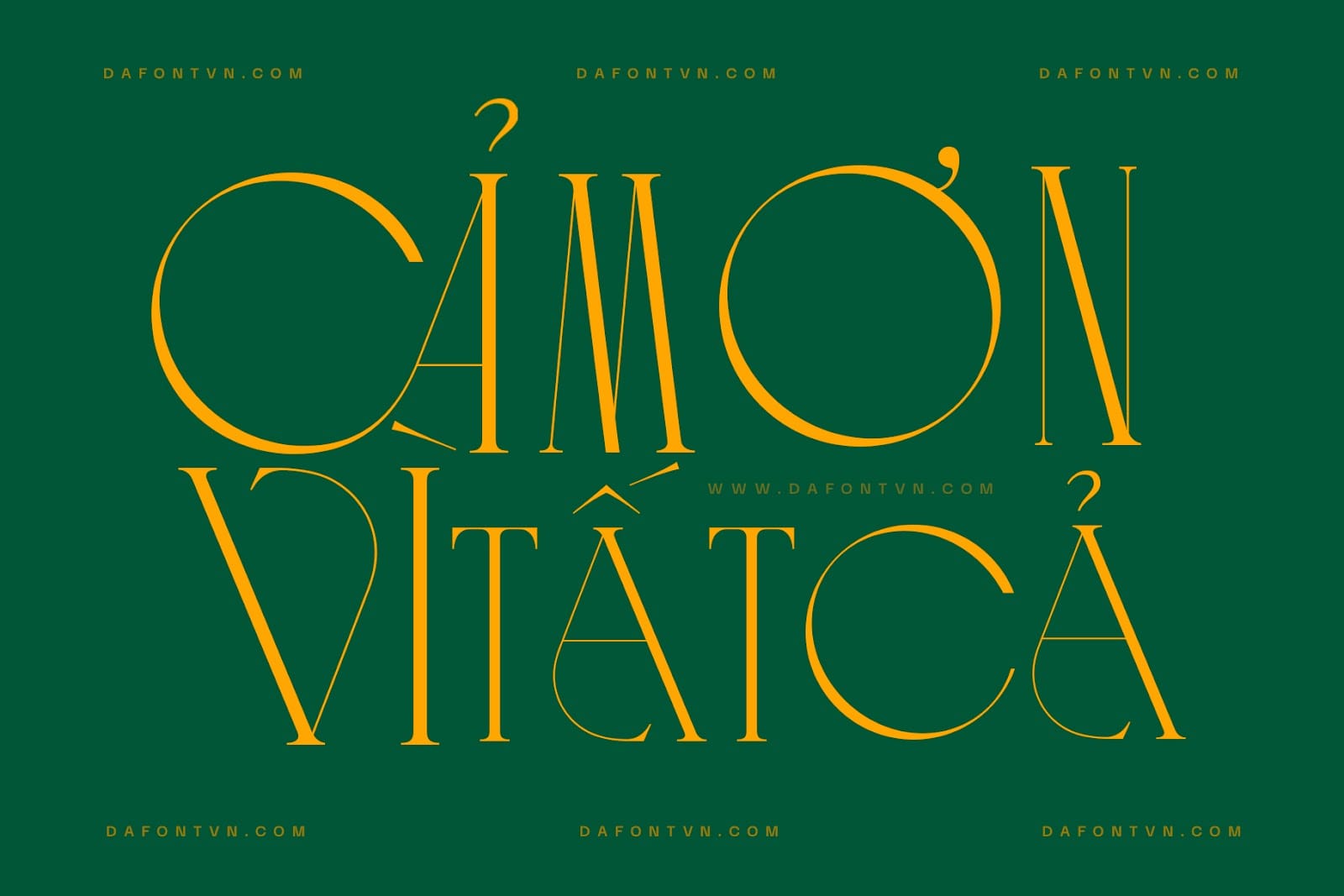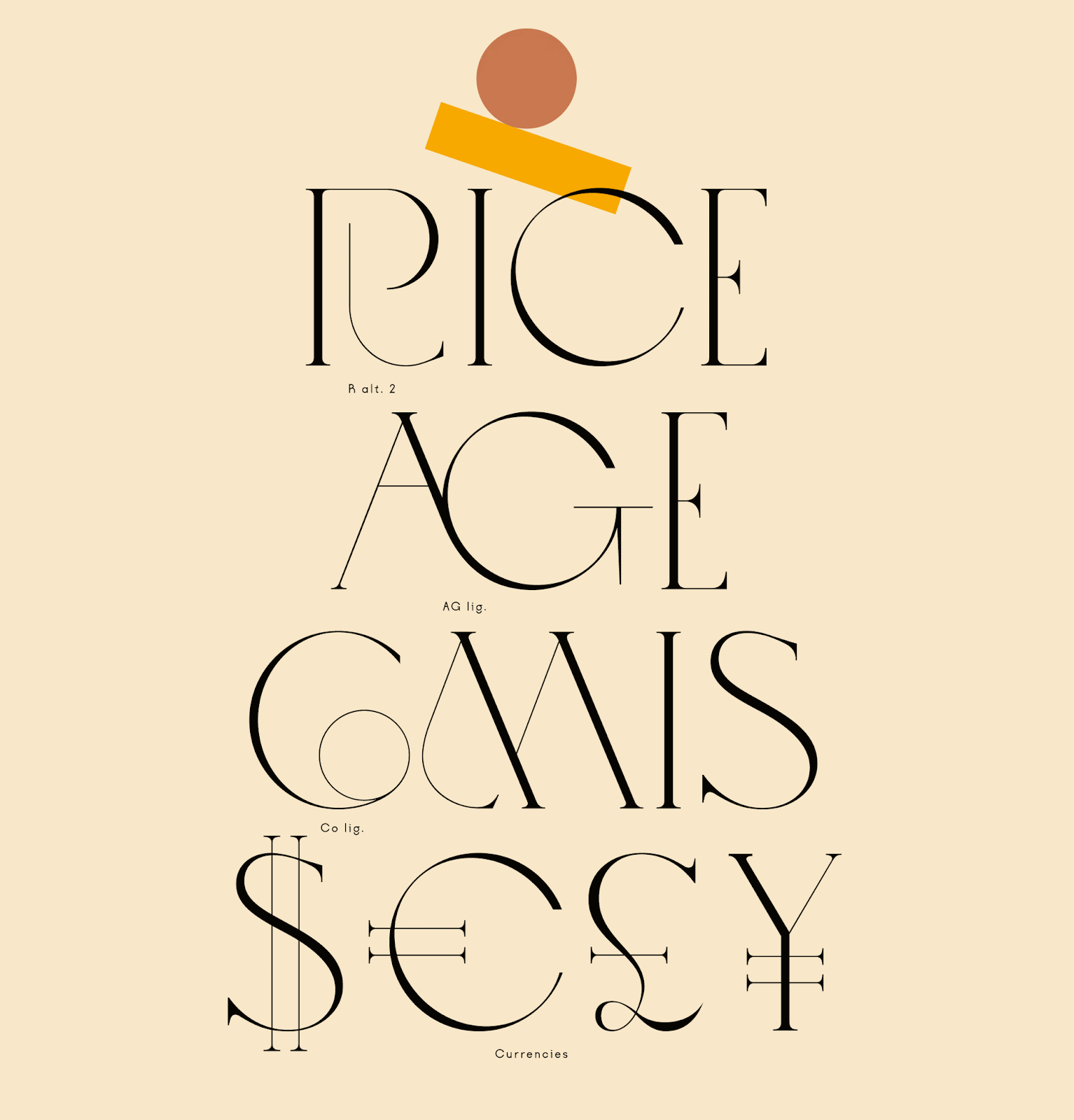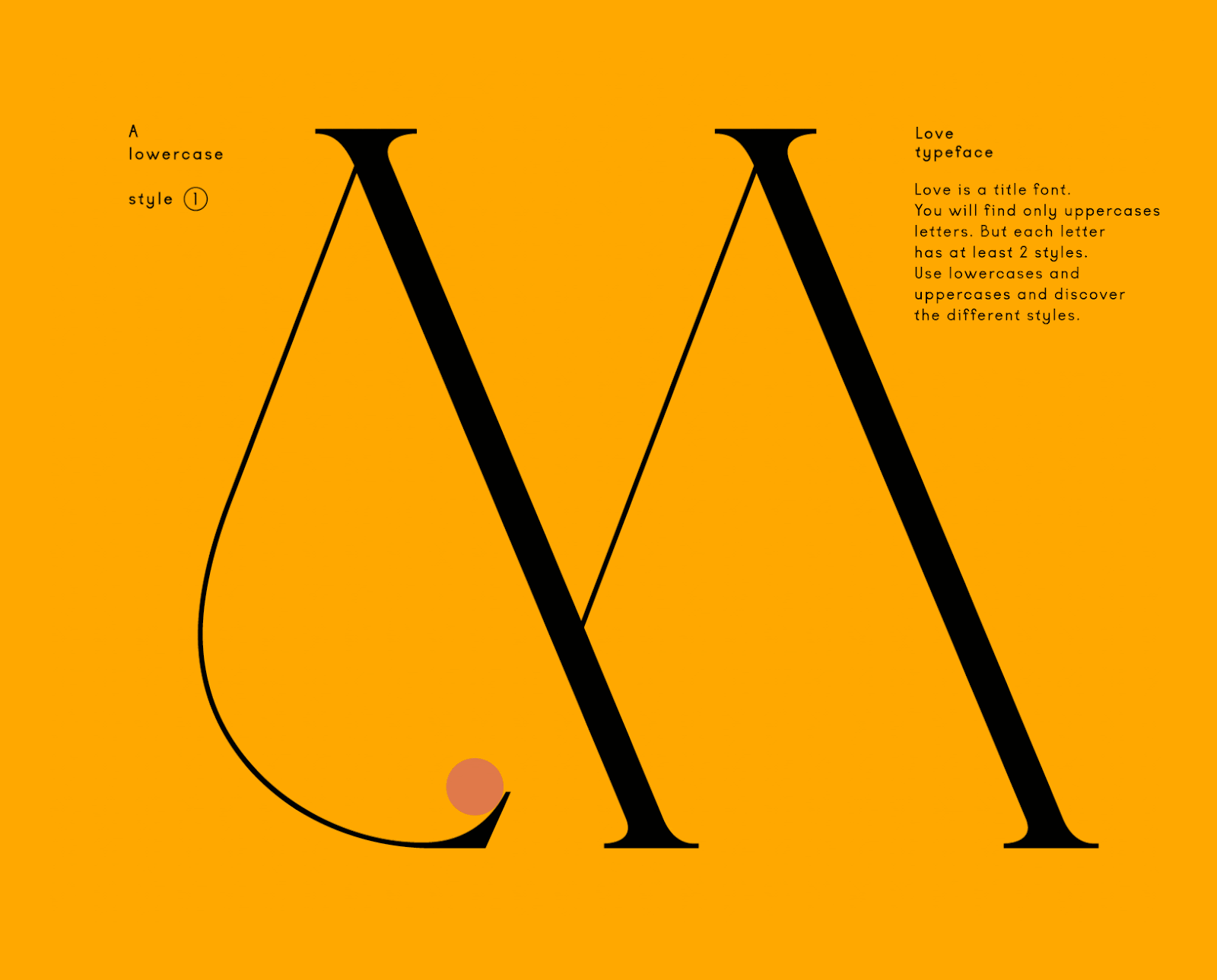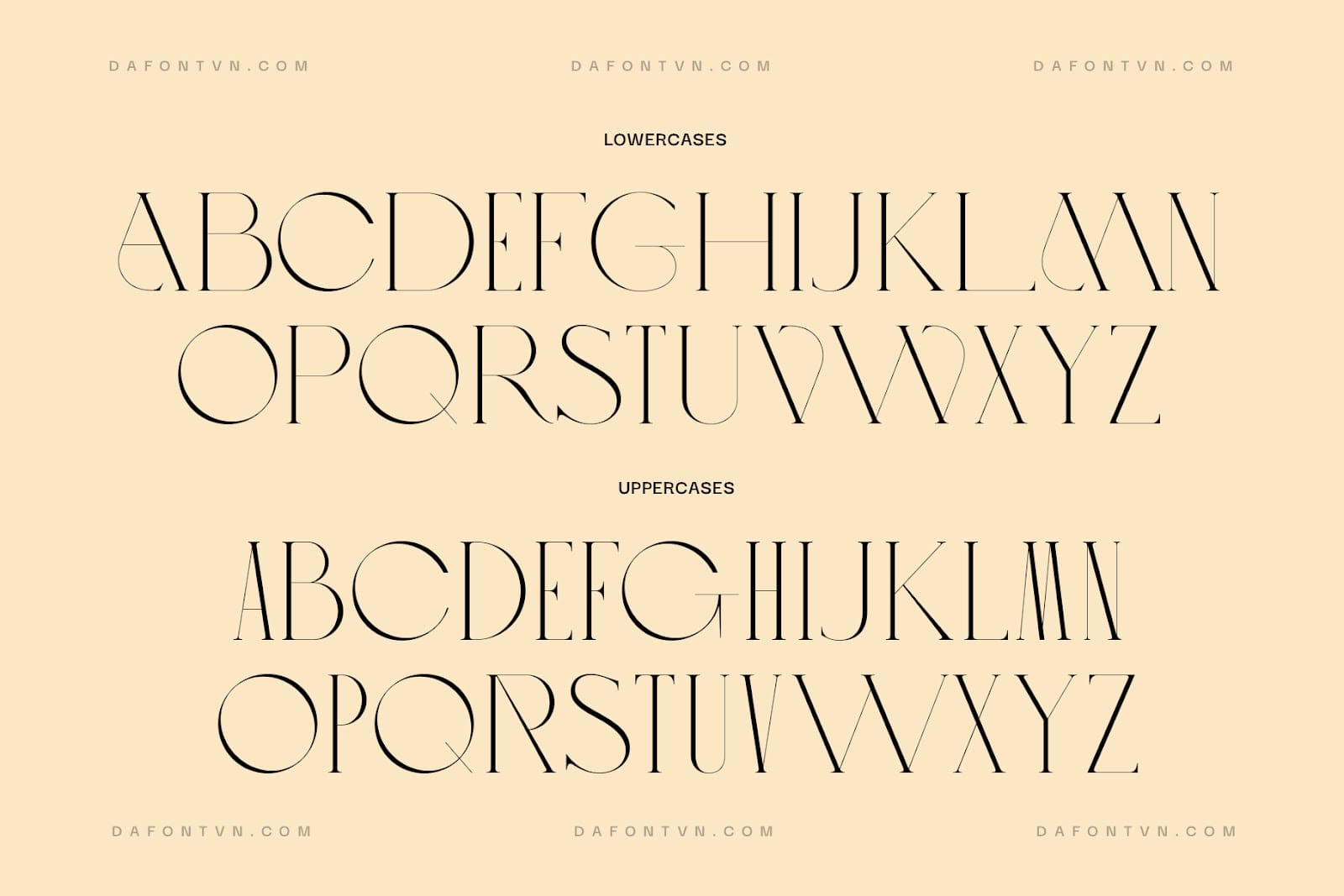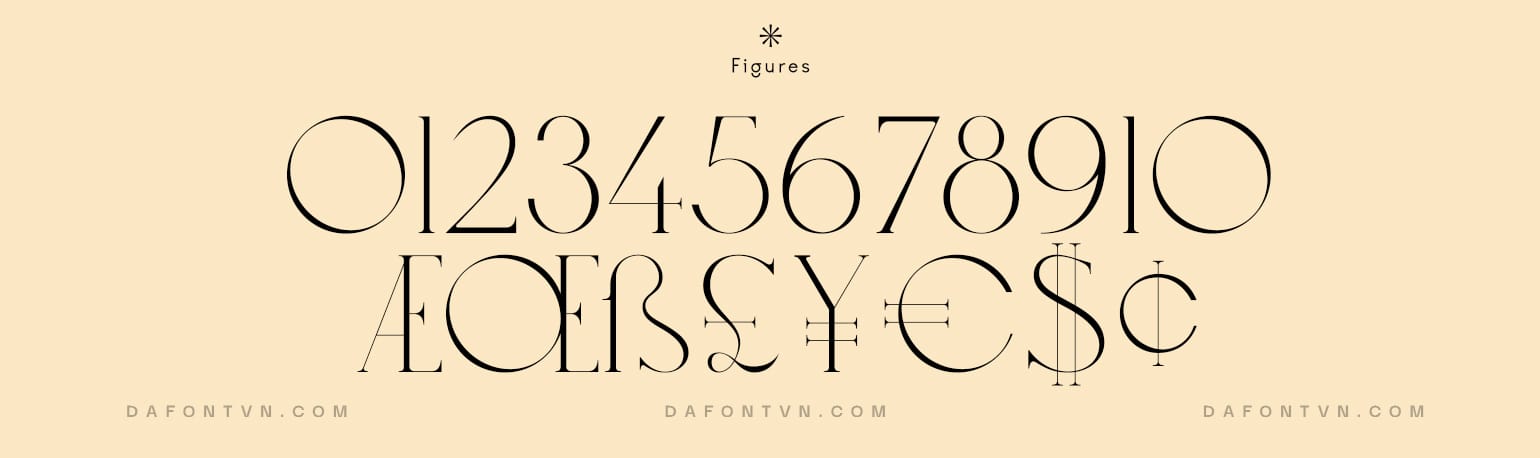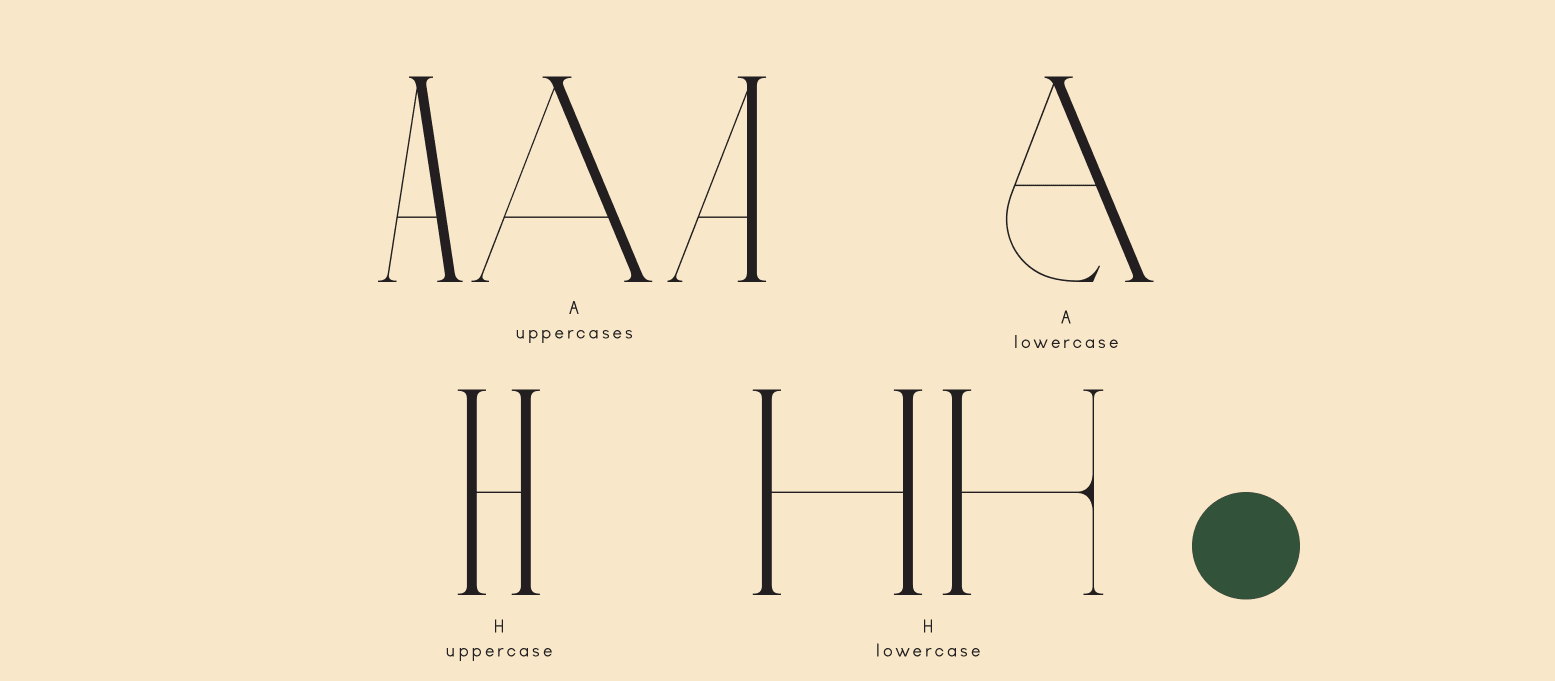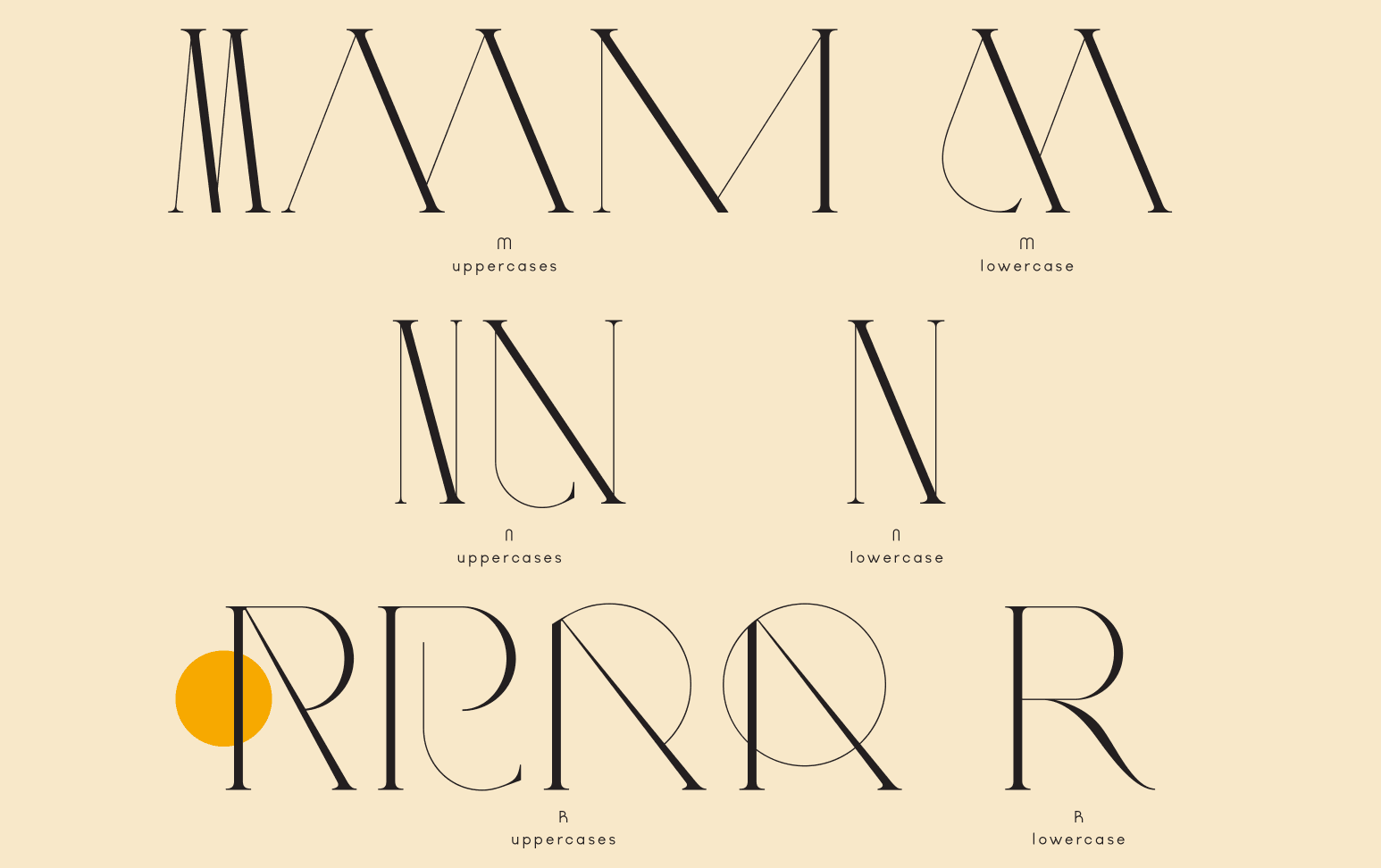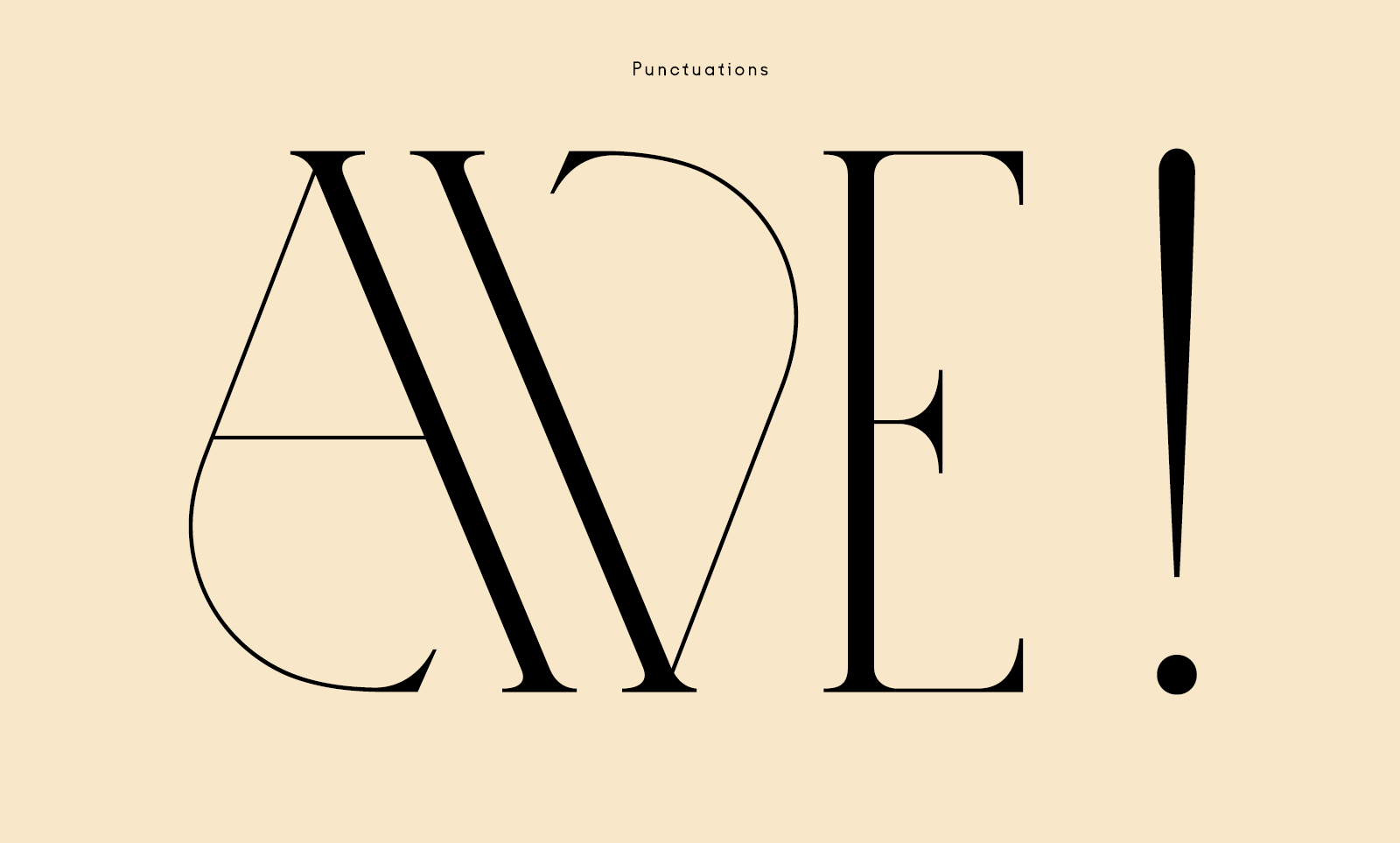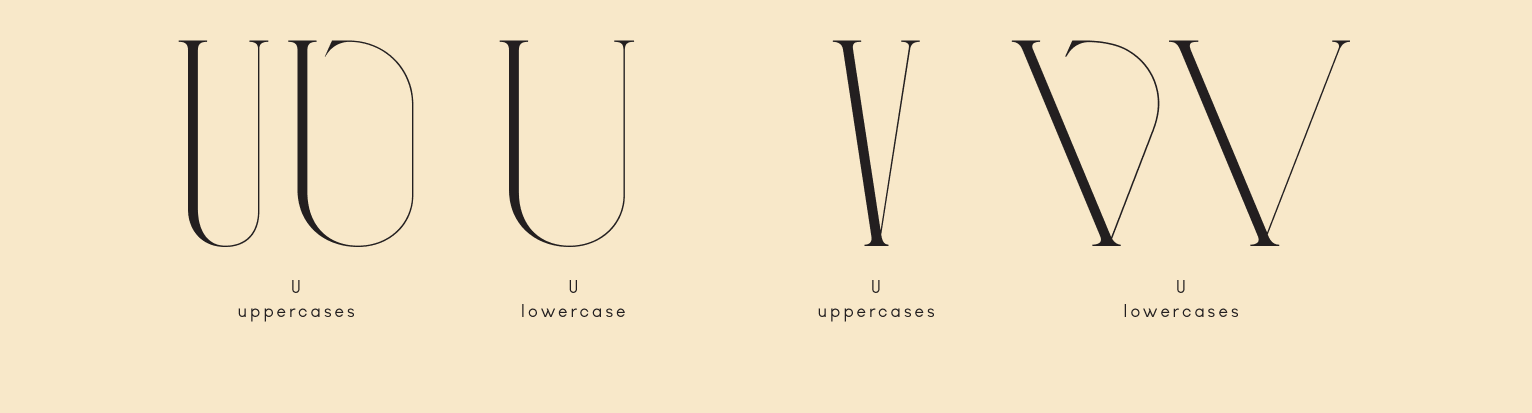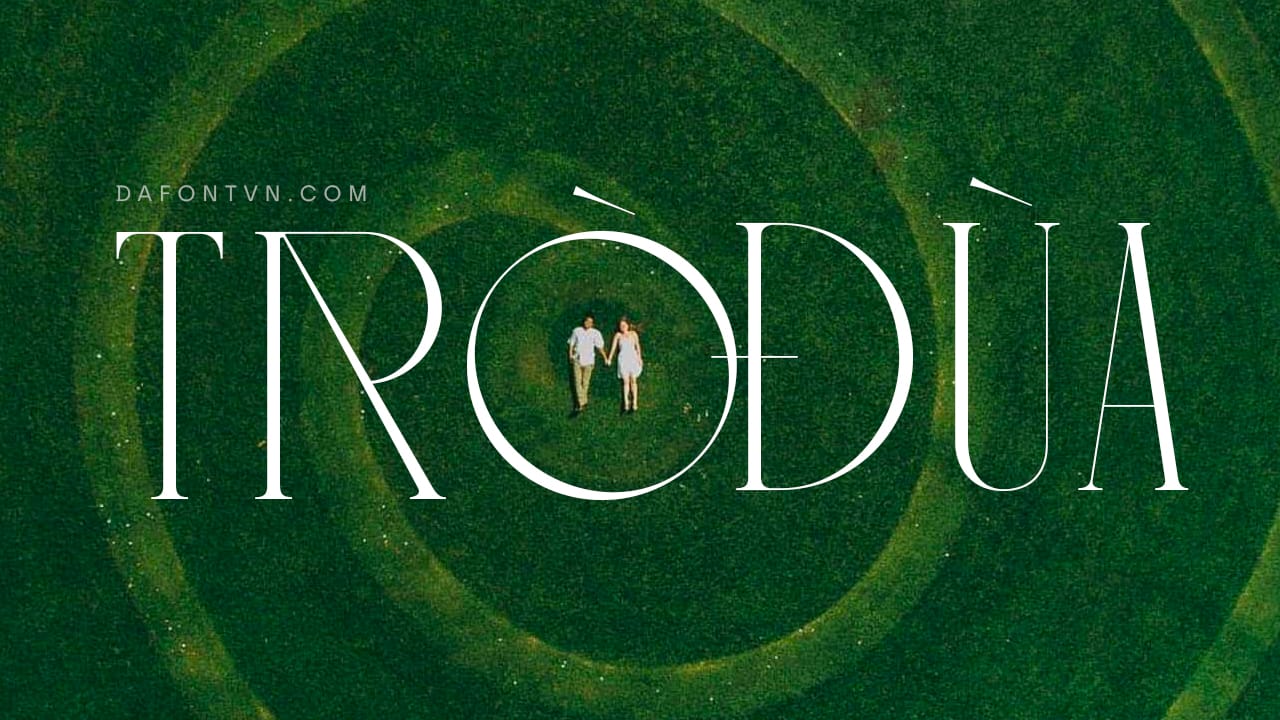
Love là một kiểu chữ in hoa toàn bộ được thiết kế vào bởi Jérémy Schneider và được xuất bản thông qua VJ-Type vào năm 2018 với mỗi chữ cái có ít nhất hai kiểu. Một số thậm chí có nhiều lựa chọn thay thế đẹp mắt hơn.
Phông chữ này được lấy cảm hứng từ ban nhạc Love của Mỹ và đặc biệt từ album tuyệt vời năm 1967 của họ mang tên Forever Changes. Các chữ cái của nó mang đến sự tương phản đẹp mắt nhờ các nét chữ ấn tượng kết hợp với hình dáng cong tròn quyến rũ và thanh mảnh của font chữ, tạo ra nhiều nhịp điệu khác nhau bằng cách nào đó giữ được sự cân bằng giữa các typeset. Bạn sẽ vô cùng hài lòng khi sử dụng nhiều lựa chọn khác nhau trong bộ font để tạo ra nhịp điệu trầm bổng và cân bằng trong từng câu chữ.
Love là một kiểu font phù hợp cho tiêu đề, mặc dù là kiểu chữ in hoa toàn bộ nhưng bạn sẽ thấy giữa chữ hoa và chữ thường có ít nhất 2 phong cách khác nhau, hãy thử kết hợp để tạo ra các thiết kế phá cách hơn nhé.